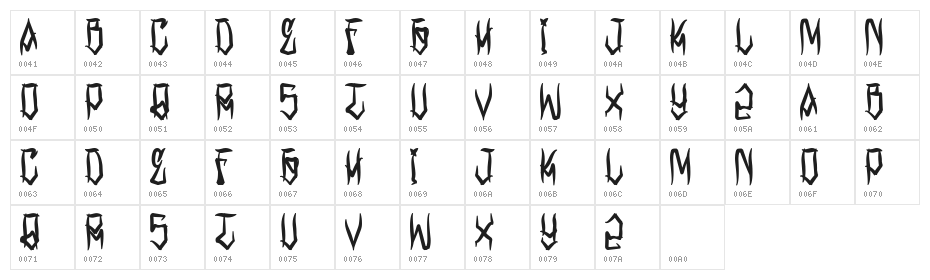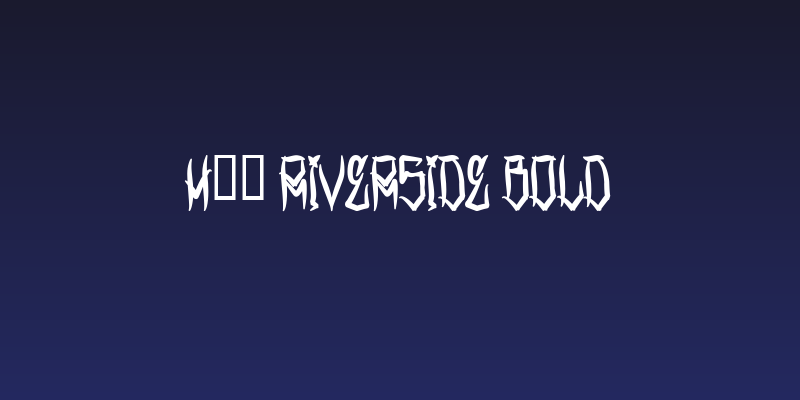
H74 Riverside Bold Font
✎ Gothic
| Stile generale | Gothic, Edgy, Avant-garde |
| Progetti proposti | Ideal for album covers, posters, and branding that require a strong, rebellious aesthetic. |